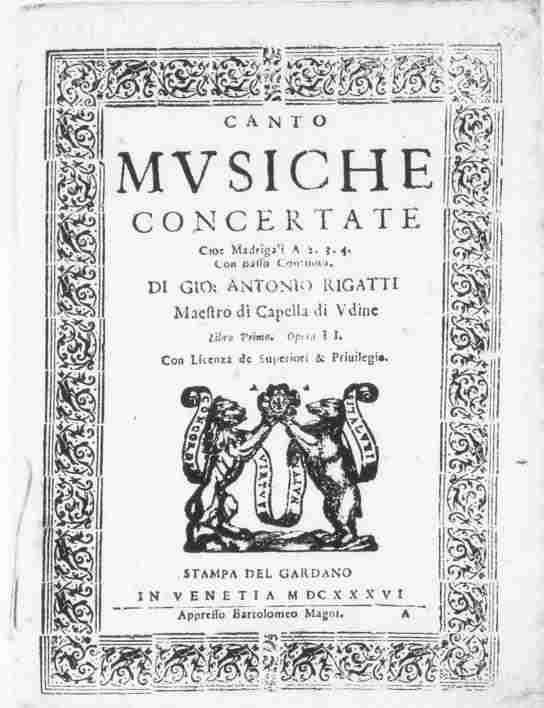
dc> Comment s'appellent ces ornements qui servaient à décorer une page de
titre
dc> ou une table?
des vignettes, des éléments de cadre...
dc> Est-ce qu'il en existe des versions électroniques, soit dans une police,
oui, Caslon Ornaments, p. ex. (qui reproduit des vignettes à la
Fournier), ou Caravan LH pour qqch de plus géométrique, il y en a dans
les catalogues de tous les fondeurs.
dc> soit sous forme graphique,
ça se trouve aussi en EPS, parfois
dc> qu'on pourrait piocher quelque part?
Il y en a sûrement sur apostrophic labs